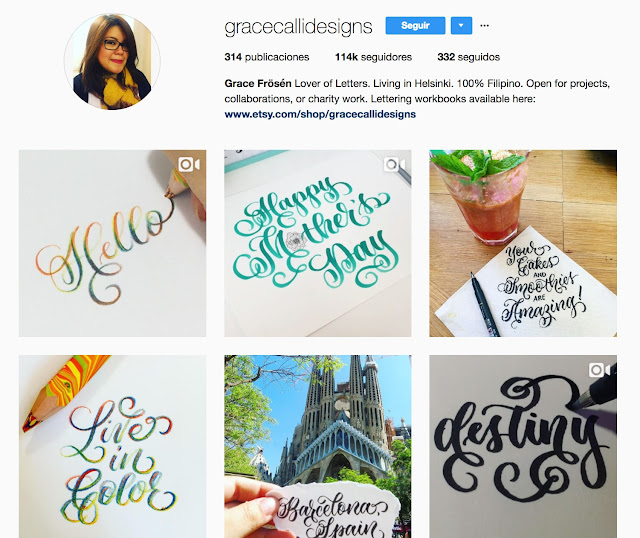
Su habilidad para la caligrafía hipnotiza al mundo entero, sus videos realizando caligrafía tradicional y digital arrasan en Instagram donde le siguen mas de 114.000 seguidores, y es raro que no hayas visto uno de sus videos convertidos ya en virales, ella es Grace Frösén, hace poco que ha visitado España y en Lettering Time tenemos el placer de haberle realizado una entrevista para que podamos disfrutar todos de sus amables palabras:
Hola Grace, bienvenida a Lettering Time, cuéntanos ¿Como empezaste en el mundo de la caligrafía? ¿Que significa la caligrafía para ti?
Comencé cuando estaba planeando mi propia boda y ahí es donde descubrí la asombrosa caligrafia de las invitaciones. Pense para mi misma: "Tal vez puedo realizar yo mis propias invitaciones!" Estuve unos seis meses para aprender este tipo de caligrafia antes de enviar las invitaciones, y para ello compre libros, mire videos en internet y practique. ¡Ya no he parado desde entonces!
Si no me equivoco, vives en Helsinki pero de origen Filipino ¿Como se entiende la caligrafía en Finlandia?¿Es algo valorado allí?¿Se entiende que es una disciplina que debe ser preservado o como algo que está desactualizado e inútil?
La caligrafía en Finlandia no es algo muy popular, pero creo que esta en aumento. Si existe una comunidad alrededor de la caligrafía, y hay diferentes foros y convenciones cada año. Pero esta caligrafía que se practica esta muy arraigada en el estilo tradicional, yo por el contrario tengo un estilo mas moderno y espero que la comunidad también sea mas inclusiva en este sentido. El arte en general es muy apreciado en Finlandia.
En tu perfil de Instagram tienes más de 114.00 fieles seguidores en estos momentos, tus videos y fotos tienen decenas de miles de visualizaciones, "Me gustas" y comentarios ¿Qué te supone esta red social?¿Ayuda realmente a obtener mas proyectos o clientes?
Si, tengo mucha suerte de tener a todos estos seguidores que aprecian a diario mi trabajo. Tener una amplia audiencia si me ha ayudado a obtener mas clientes, proyectos e ¡incluso amigos! Estoy muy agradecia a Instagram y cada que ha compartido mi trabajo. Sin ellos, mi trabajo no sería nada.
Muchas de tus publicaciones son con rotuladores con punta de pincel o pinceles tradicionales ¿Qué consejos le darías a aquellos amigos que están empezando en este tipo de caligrafía?
Mi consejo es practicar todos los días. Muchas personas que empiezan se acaban frustrando porque es mas difícil de lo que pensaban, y cuando no les sale como pensaban creen que ya están fallando en la caligrafía. Pero todo eso es parte del proceso. Ellos solo tienen que ir acostumbrándose a los trazos, ir entrenando los músculos de la mano. Así que sobre todo necesitan paciencia, aceptar que se van a cometer errores, y simplemente disfrutar del proceso.
De vez en cuando, subes videos donde realizas caligrafia digital con el Ipad los cuales han tenido un gran éxito ¿Qué diferencia encuentras entre este nuevo sistema de realizar caligrafía y la caligrafía tradicional?
A menudo la gente piensa que la caligrafía digital es automática, y cuando ven que haces líneas gruesas y finas, piensan que el Ipad ajusta esto automáticamente, pero tienes que saber cuándo ejercer la presión y cuando no. El Ipad utiliza los mismos principios que la caligrafia tradicional, pero de alguna manera también es mas cómodo porque no tienes que lidiar con los derrames o manchas de tinta, no pierdes mucho papel, puedes hacer zoom para añadir pequeños detalles y, lo mas importante, puedes hacer click en "deshacer" si cometes un error.
Entiendo que usas Ipad Pro y un Apple Pencil, pero nuestros seguidores me matan si no te pregunto qué programas utilizas o cuales son tus aplicaciones favoritas para realizar la caligrafia digital.
Normalmente uso la aplicación Procreate, ¡es asombrosa! Son alrededor de 6 dólares, pero tiene un montón de opciones de pincel, puedes utilizar capas y otros efectos, es una aplicación realmente genial para el dibujo y la caligrafía. También uso las aplicaciones de Adobe porque pueden dibujar vectores y puedo transferirlo al Photoshop o Illustrator en mi Mac. Hay otras aplicaciones divertidas como Amaziograph que puedes usar para crear mandalas.
¿Crees que estos dos tipos de caligrafia (digital y tradicional) pueden coexistir al mismo tiempo sin problemas o por el contrario el uno "mata" al otro?
Si lo creo. Pienso que siempre hay espacio para todos los estilos. Sólo porque surja algo mas moderno no significa que va a destruir la forma tradicional. Incluso con la tecnología moderna y las aplicaciones, mucha gente todavía sigue utilizando plumillas y tinta. Pienso que la tecnología moderna realza el arte y da a las personas mas opciones.
¿Qué le dirías a aquellas personas que dicen que la caligrafía con el Ipad no es caligrafía?
¡Quiero decirles que gracias por mantener viva a la comunidad de la caligrafía y gracias también por apreciar este arte!